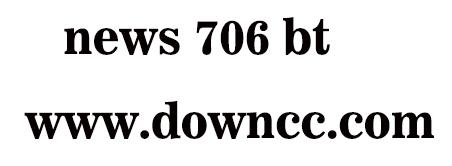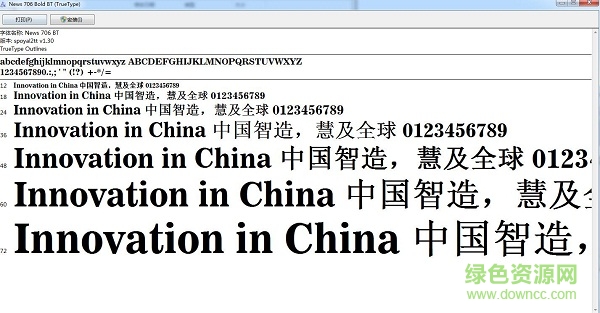
軟件介紹 軟件標簽: news字體 英文粗體 news 706 bt bold字體是一款粗體英文襯線字體,字體的形態(tài)結構設計得十分美觀,線條干凈,靜中寓動,表現力強,歡迎大家在綠色資源網免費下載!news706bt-粗體特點字型飽滿,新結構錯落有序,印刷效果清晰明快,風格獨特,又符合字體構形規(guī)律,適合排各類標題及廣告設計。相關字體推薦newsgoth bt-普通 授權:免費軟件 WinAll大?。?00KB語言:中文newsgothbt-普通字體是一款英文襯線字體,這款字體和newsgothcnbt的不同之處就是字距要更寬闊一些,顯得明朗清晰,適合正文和小標題排版,歡迎大家在綠色資源網免費下載!字體的結構特征【單體字】:一個偏旁單獨構下載地址newsgoth bt-普通 授權:免費軟件 WinAll大?。?00KB語言:中文newsgothbt-普通字體是一款英文襯線字體,這款字體和newsgothcnbt的不同之處就是字距要更寬闊一些,顯得明朗清晰,適合正文和小標題排版,歡迎大家在綠色資源網免費下載!字體的結構特征【單體字】:一個偏旁單獨構下載地址news706bt字體安裝方法方法一:控制面板/字體/文件/安裝新字體;方法二:直接將字體復制到C:\WINDOWS\Fonts。方法三:針對win7系統(tǒng),用戶只需選中字體右鍵安裝即可。 軟件截圖 上一張下一張(1 / 1) 安裝詳細截圖 其他版本下載 標題 大小 更新日期 下載 下載地址 電腦版 news706btboldc 字體 點擊報錯 軟件無法下載或下載后無法使用,請點擊報錯,謝謝! 關閉報錯反饋 請描述您所遇到的錯誤,我們將盡快予以修正,謝謝! *必填項,請輸入內容 本類最新 sounso beauty字體 spyced哥特英文字體 ttf版 zerodegrees字體 the next font ttf版 coolvetica font keep calm ttf 免費版 相關文章 俠客風云傳攻略 我叫mt4哪個職業(yè)輸出最高 我叫mt4輸出最高的職業(yè)排行 非人學園哪個英雄厲害 非人學園最強英雄排行推薦 Windows2003 中怎樣配置NAT服務器? Linux系統(tǒng)下Telnet服務器配置 ASP.NET開發(fā)必須養(yǎng)成的編程習慣 用戶評論 熱門評論 最新評論 發(fā)表評論 查看所有評論(0) 昵稱: 請不要評論無意義或臟話,我們所有評論會有人工審核. 字數: 0/500 (您的評論需要經過審核才能顯示)